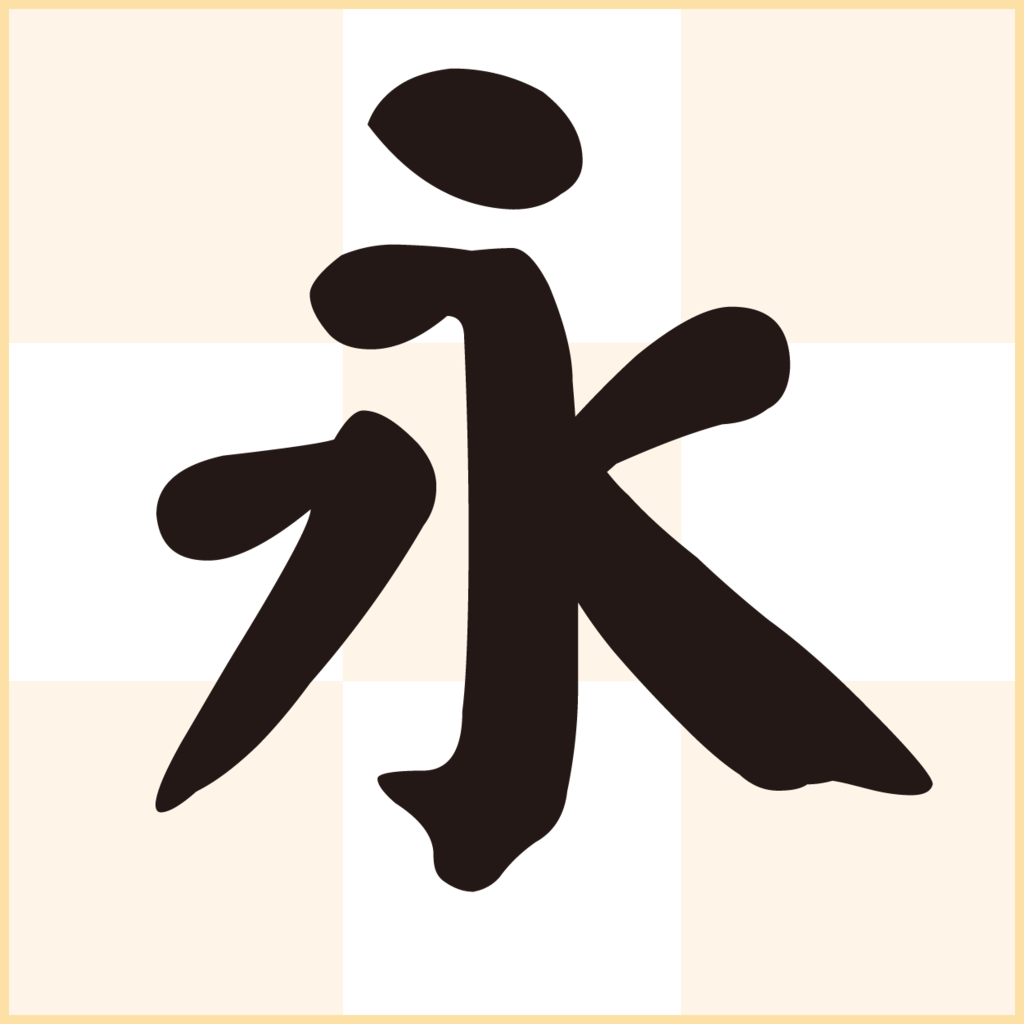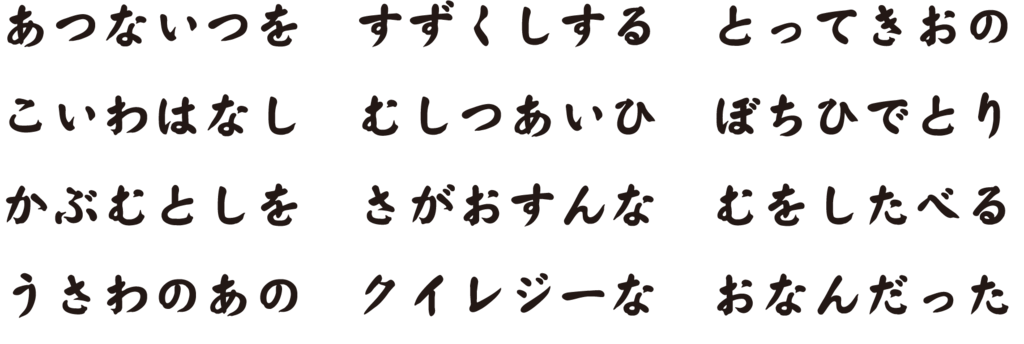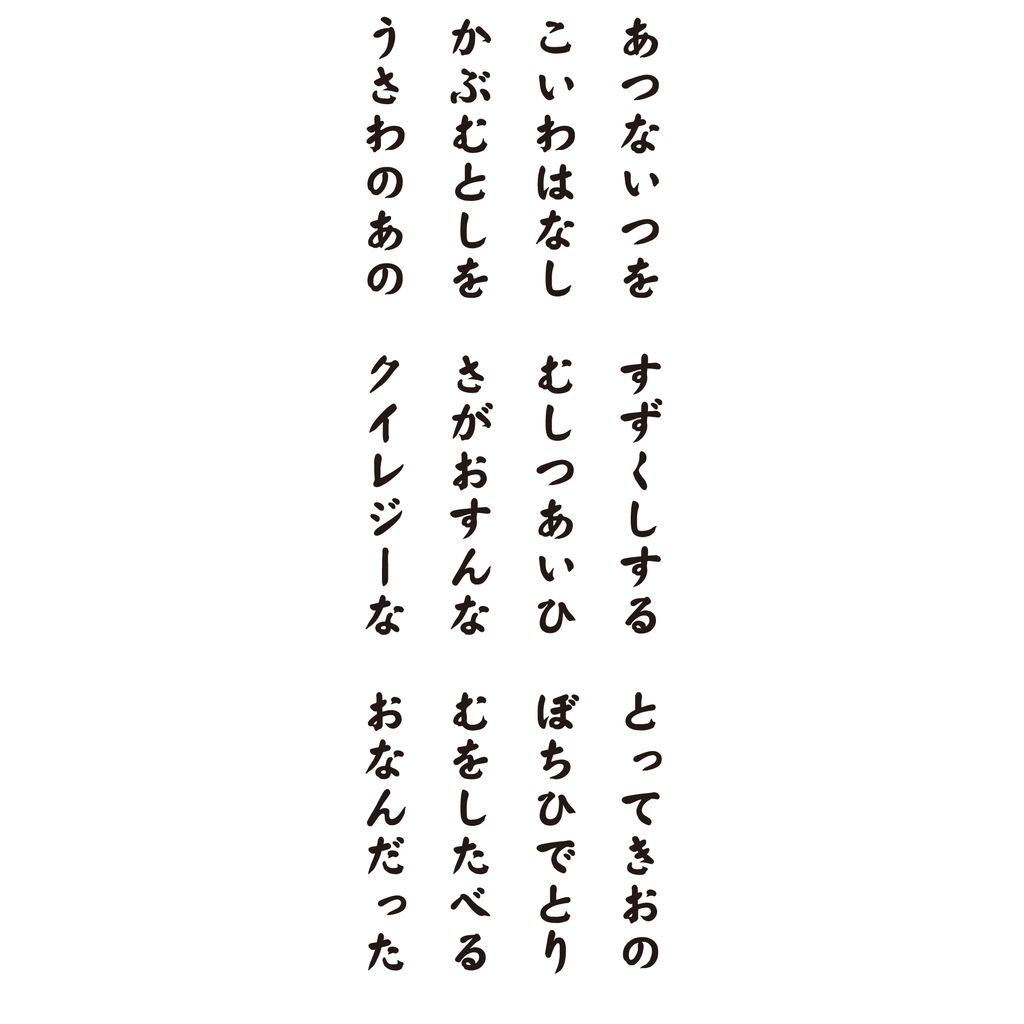
顔楷書
初唐を代表する書家・顔真卿の雄大で意気盛んといわれた書の特長を再現したデジタルフォント。起筆や右ハライの終筆部など書家独特の処理を施している。漢字の大らかで、かつどっしりした重量感に合わせ、ひらがな・カタカナもフトコロを広くとり、外側へ線を張るデザインにしてある。
顔楷書は上品で端正なスタイルながら、雄渾なストロークと伝統的な筆墨の楷書特有の趣を持ち合わせた唐の書家・「顔真卿」の楷書をモチーフにした楷書体。終筆部分には毛筆の柔らかい質感が表現されている。
顔真卿の楷書
顔真卿は初唐以来の流行である王羲之流の書法に反発し、蔵鋒の技法を確立している。その楷書の書法は力強さと穏やかさとを兼ね備えているのが特徴。
顔真卿が貧しかった頃に屋根裏に染みた雨漏りの痕を見て、この書法を編み出したと伝承として言い伝えられている。